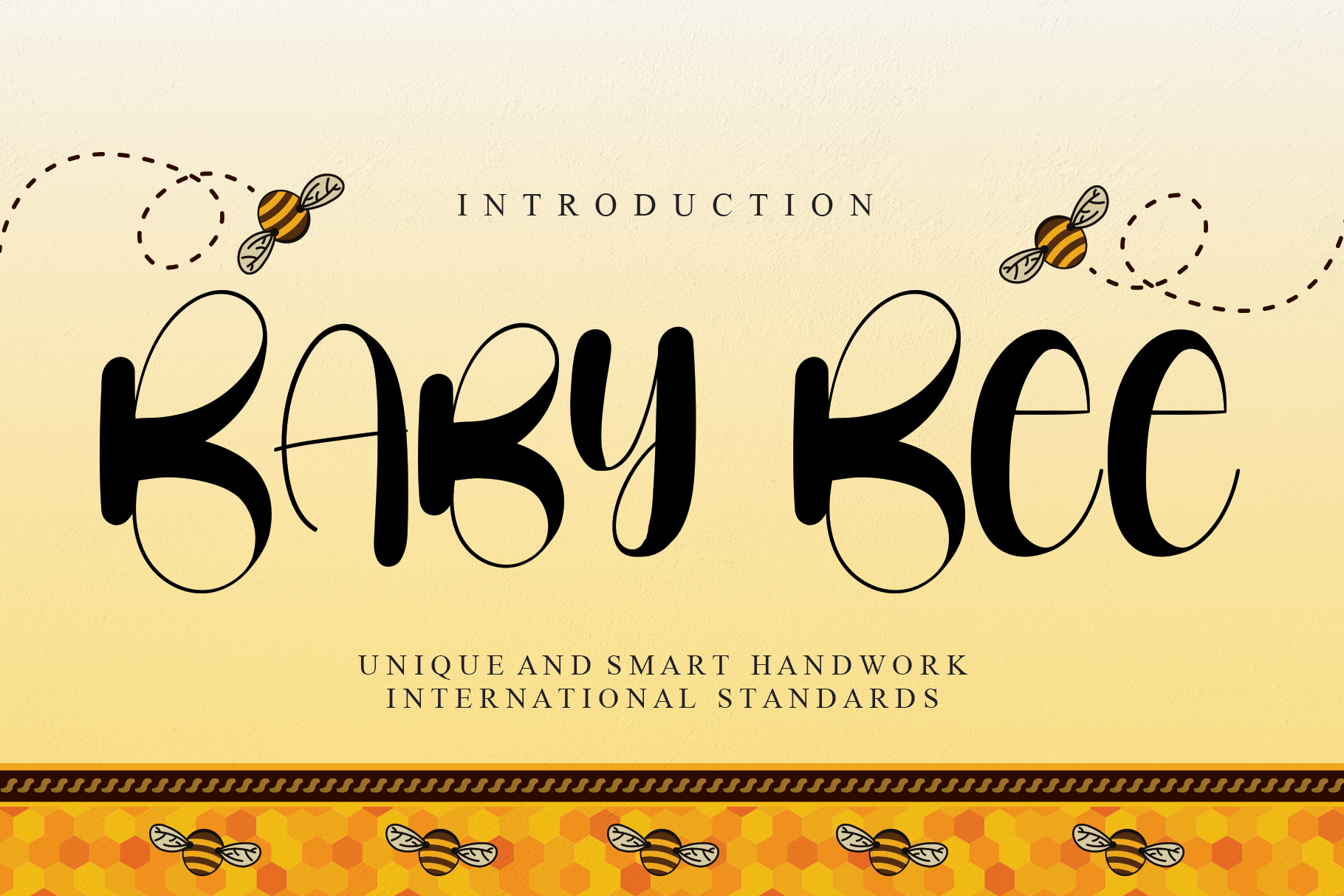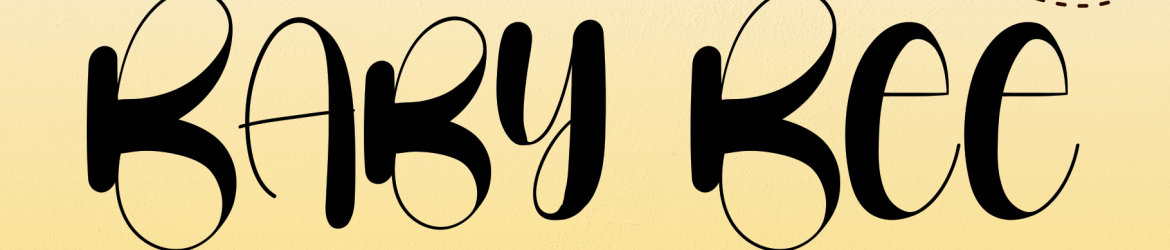
Baby Bee Script Font – Download Grátis
A ‘Baby Bee Script Font’ é uma elegante caligrafia escrita à mão que traz confiança, autenticidade e encanto para qualquer mensagem. Perfeita tanto para cartas quanto para logotipos, rótulos e muito mais, essa fonte é a escolha perfeita para quem busca um ar de sofisticação moderna em seus projetos criativos. Seja você um designer profissional ou alguém que quer adicionar um toque único aos seus trabalhos pessoais, ‘Baby Bee Script Font’ oferece a liberdade criativa necessária para expressar sua personalidade e transmitir uma mensagem com estilo. Com suas linhas suaves e formas delicadas, essa fonte se destaca como um item indispensável na sua coleção de recursos gráficos.